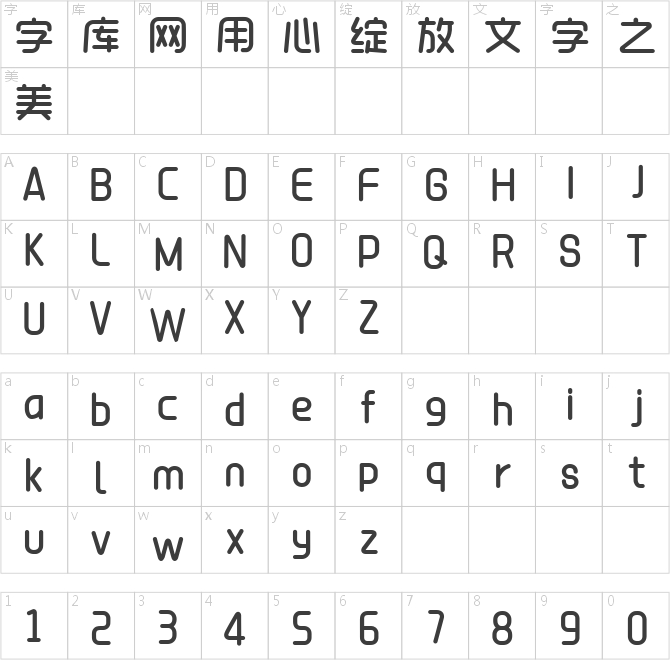
創(chuàng)客貼幼稚園體粗體
創(chuàng)客貼幼稚園體粗體字體字庫是一款讓人賞心悅目、百看不厭的中文字體,適合各類廣告和產(chǎn)品包裝設(shè)計應(yīng)用,字體大小5.94MB,格式為ttf字體,上傳用戶是創(chuàng)客貼在線設(shè)計工具,作者/版權(quán)方為創(chuàng)客貼